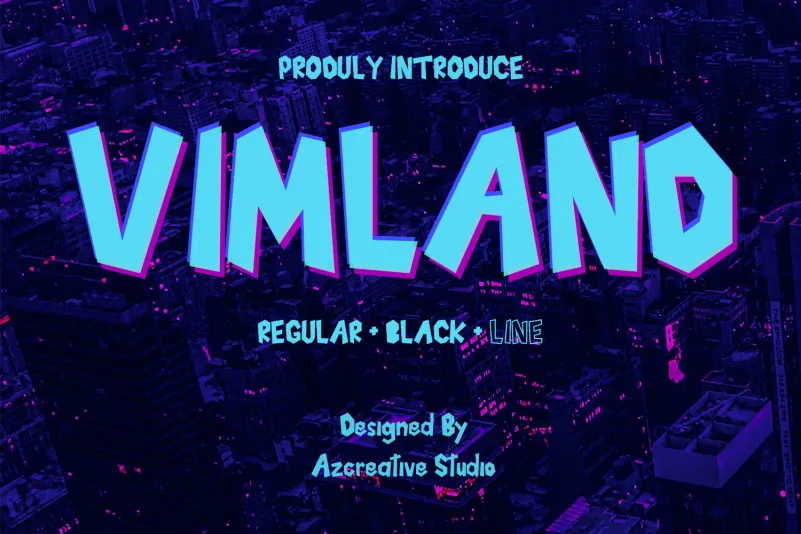
Vimland Font – Download Grátis
A Vimland Font é uma escolha perfeita para projetos modernos e tecnológicos. Esta tipografia em estilo display não só destacará seus designs com sua elegância robusta e letras grossas, como também traz um toque de modernidade e sofisticação aos seus projetos. Composta sobretudo para ambientes que valorizam uma postura futurista, a Vimland é perfeitamente adequada para criações em áreas como design de gráficos digitais ou interfaces de usuário, onde o impacto visual e a capacidade de se destacar são essenciais. Esse é um verdadeiro recurso para aqueles que buscam uma fonte única para dar vida à sua criatividade no digital.
Designer: azcreativestd